모든 탐구의 시작은 물음에서부터
변화하는 환경 속에서 우리를 지탱하는 것은 본질을 탐구하려는 진심이 아닐까요? [2025 산돌 사이시옷: 타입 컨퍼런스]은 ‘탐구하는 사람들’을 주제로 다양한 탐구자들이 모였는데요. 방법은 달라도 일의 시작에는 언제나 탐구가 있음을 확인할 수 있는 자리였어요. 오늘은 지난 10월 18일 개최된 [2025 사이시옷]의 이야기를 들려드리려고 해요.
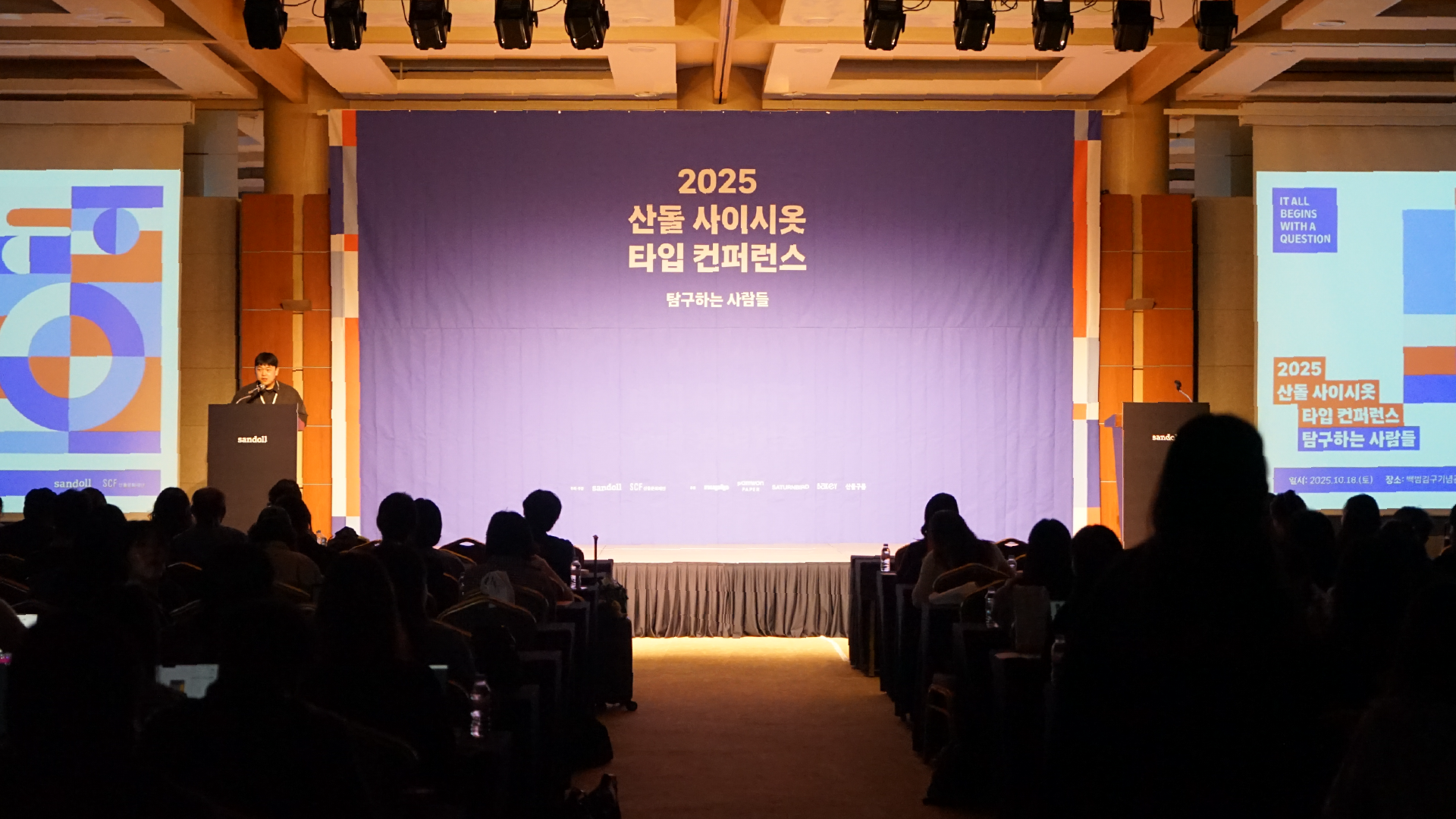
산돌은 누구나 자유롭게 표현할 수 있는 세상을 꿈꾸며 창작자들의 탐구를 지지하고 있어요. [2025 사이시옷]도 그 연장선상에서 기획됐어요. 우리의 철학을 담은 ‘탐구하는 사람들’이라는 주제는 ‘물음표’의 상징 기호로 표현했어요. 모든 탐구의 시작은 물음에서부터 시작함을 상징적으로 나타내고 있어요.
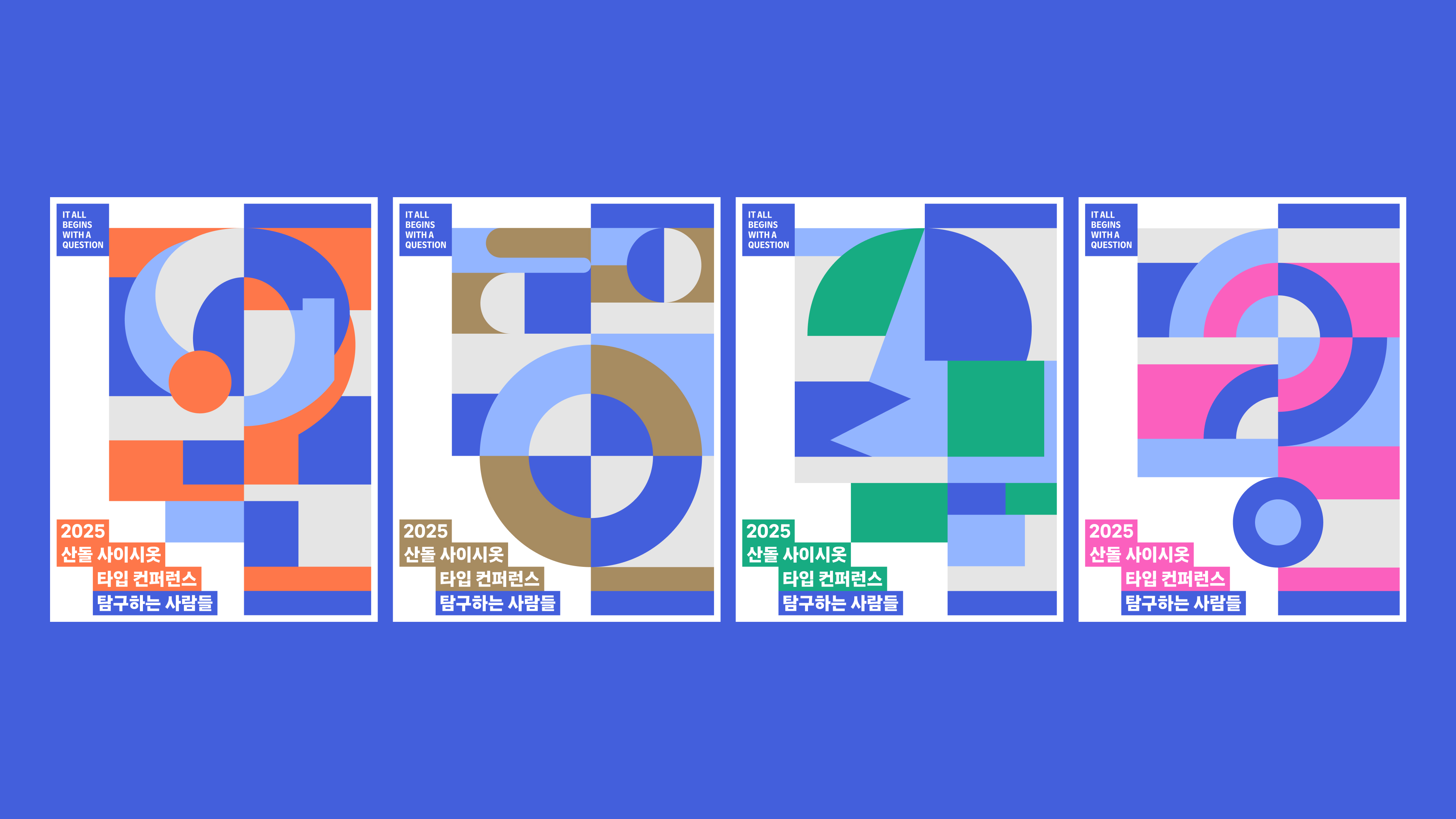
탐구자들
‘탐구’와 관련된 장치들을 행사장 곳곳에 설치했는데요. 그중 하나가 현장 등록 시스템이었어요. 특정 코드를 페이지에 심어 질문에 어떻게 답변하는지에 따라 탐구자 유형이 나뉘도록 설계했어요. 현장 등록을 마치고 나면 나의 탐구자 유형을 살펴볼 수 있었죠. 1. Risk-taker(모험가) 2. Tracer(관찰자) 3. Reframer(전환가) 4. Architect(분석가) 사이시옷의 탐구자 유형은 이렇게 4가지로 나뉘어요. 결과 페이지에서 탐구자 유형을 분석해 주고, 나와 잘 맞는 탐구자는 어떤 유형인지 제공했어요.
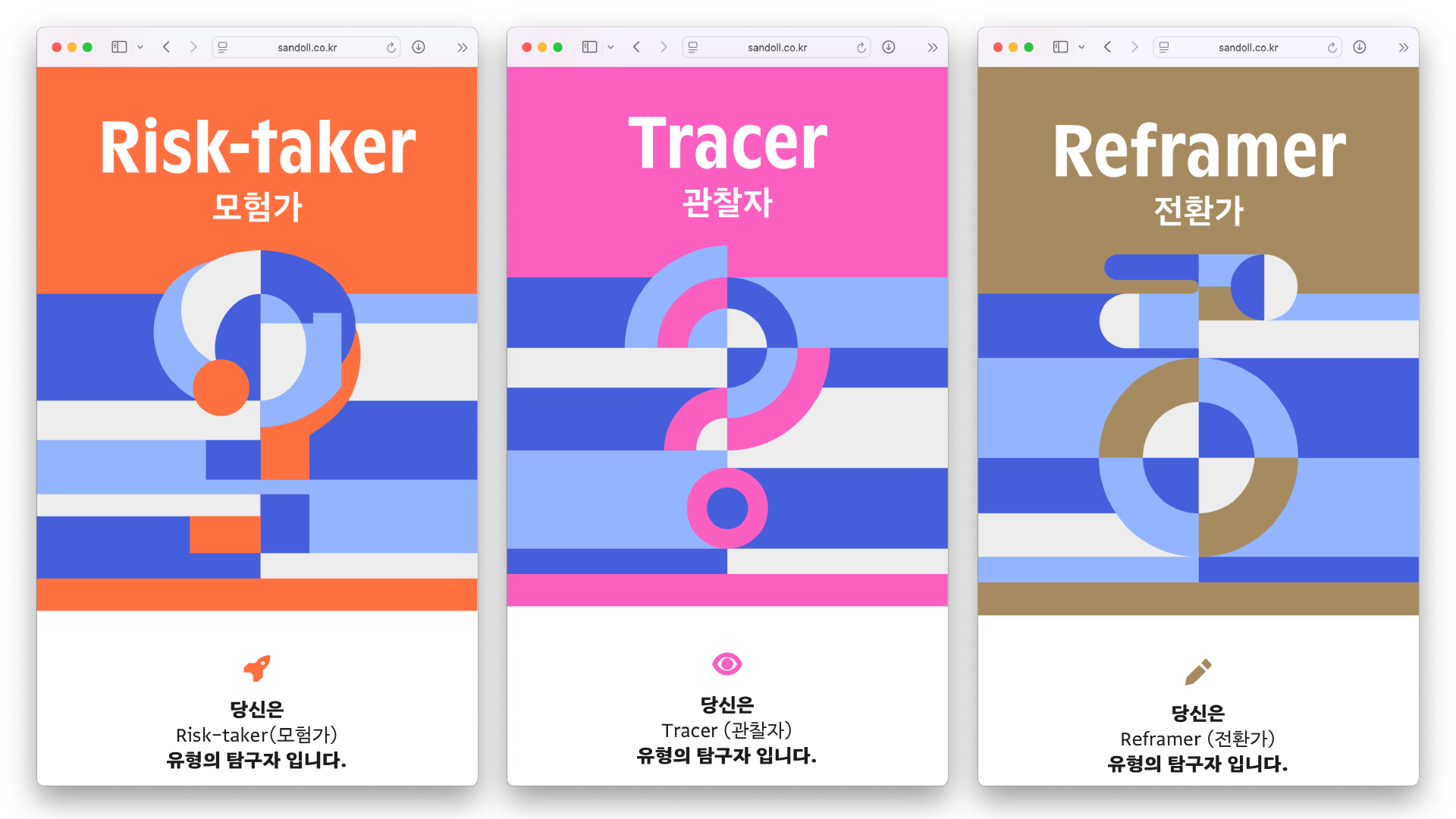
같이 탐구할까요?
[사이시옷]은 강연 외에도 다양한 방식으로 탐구의 경험을 확장하고 있어요. 참가자 간 자연스럽게 교류할 수 있는 접점을 만들기 위함인데요. 올해도 자유롭게 창작물을 부착할 수 있는 공유 보드인 ‘시옷보드’를 운영했어요. 포스터, 굿즈, 명함, 채용 정보 등 다양한 게시물들이 보드를 채웠어요. 창작물과 더불어 오늘의 다짐을 애정 어린 손 글씨로 남기며 각자의 생각을 공유하기도 했어요.
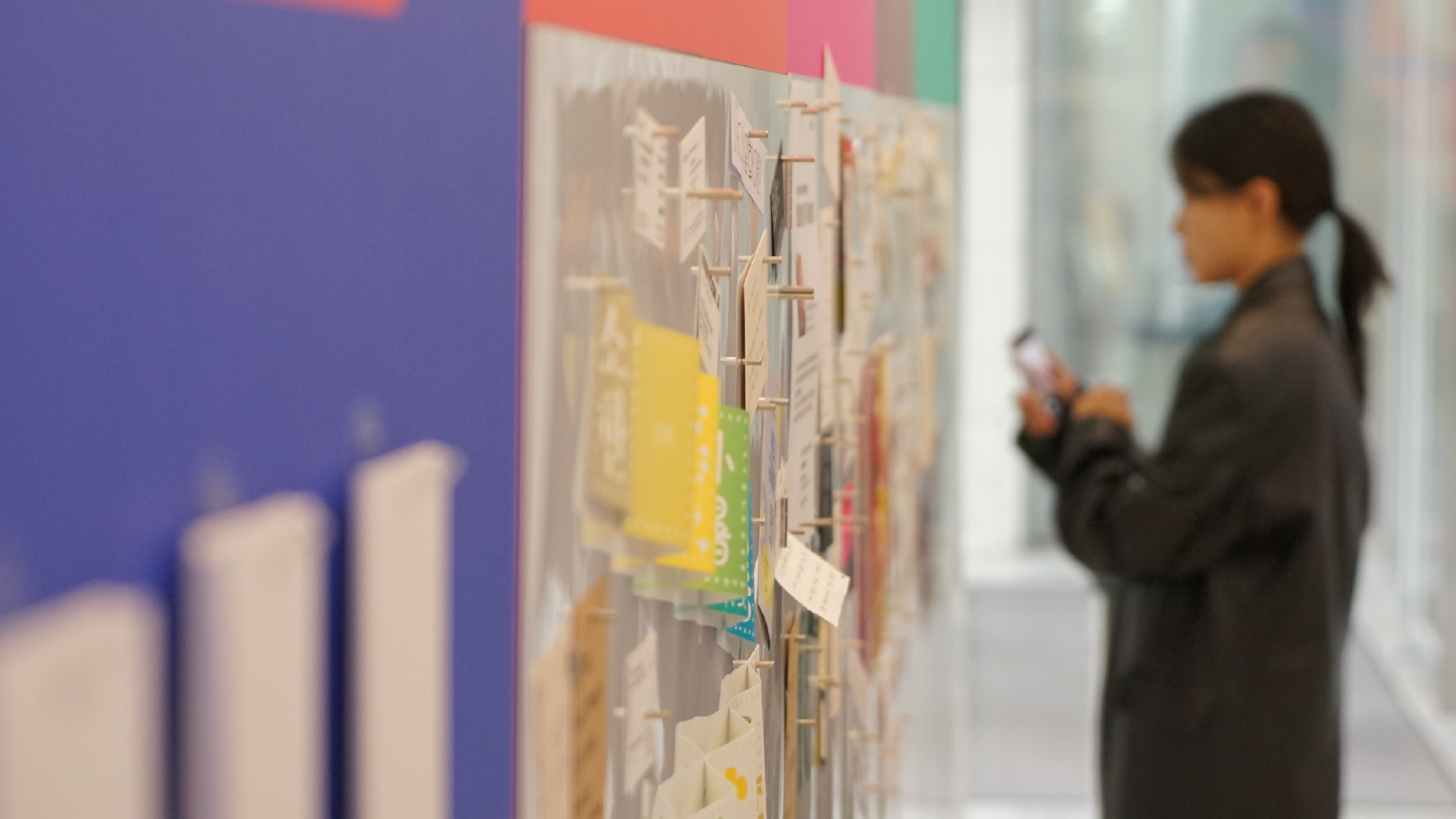
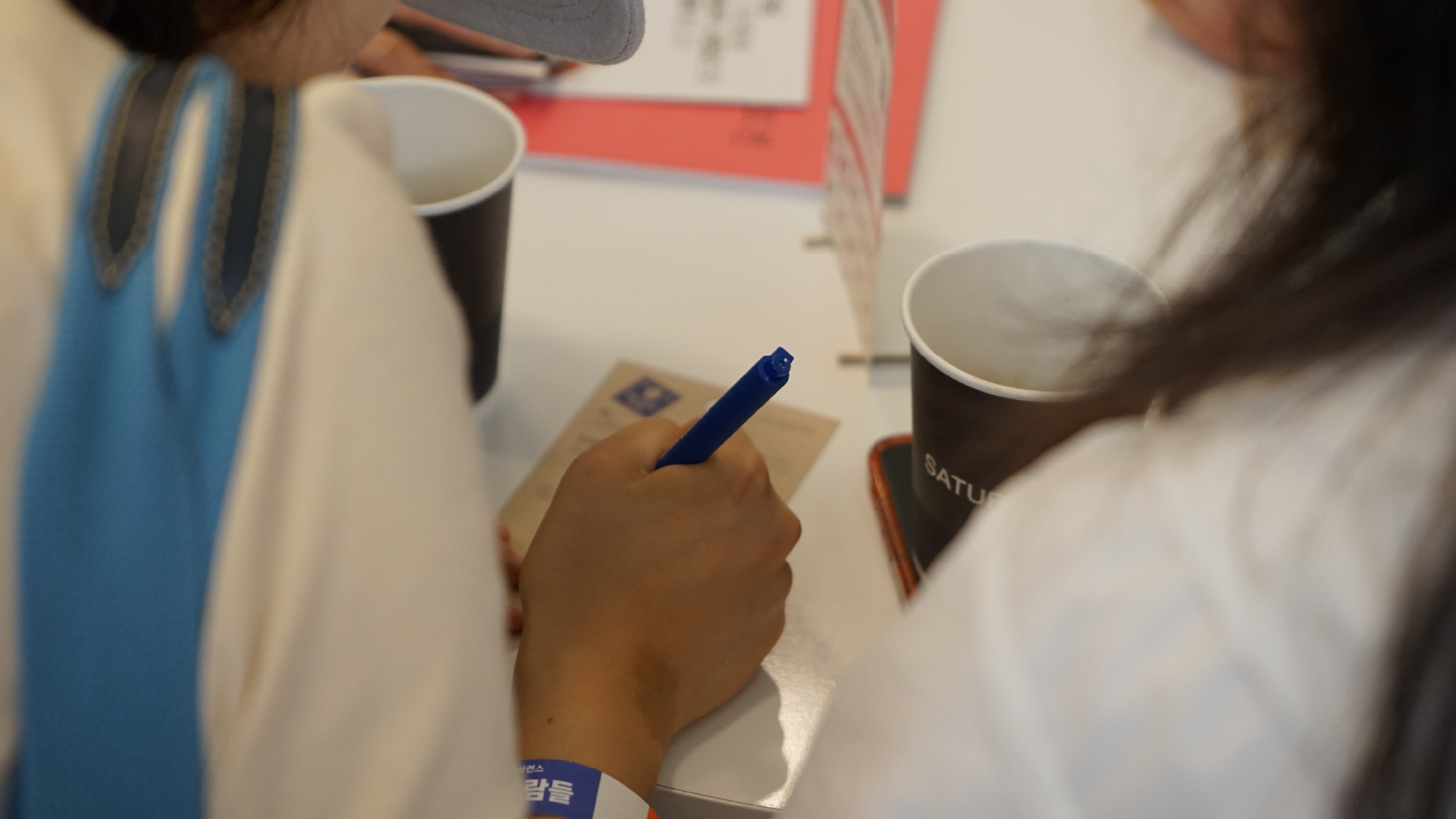
대면 네트워킹이 쑥스러운 분들을 위해 비대면으로 참여할 수 있는 장치도 마련했어요. 참가자들의 편지가 랜덤으로 교환되는 ‘레터박스’를 운영했는데요. 내가 쓴 편지를 투입하면 다른 참가자의 편지를 랜덤으로 받아볼 수 있는 시스템이에요. 서로의 얼굴은 모르지만, 같은 공간에서 같은 관심을 가진 사람들이 연결되는 경험이 묘하지 않나요? 산돌이 보유한 최첨단 인간 지능 기술로 구현할 수 있었던 ‘레터박스’였어요.
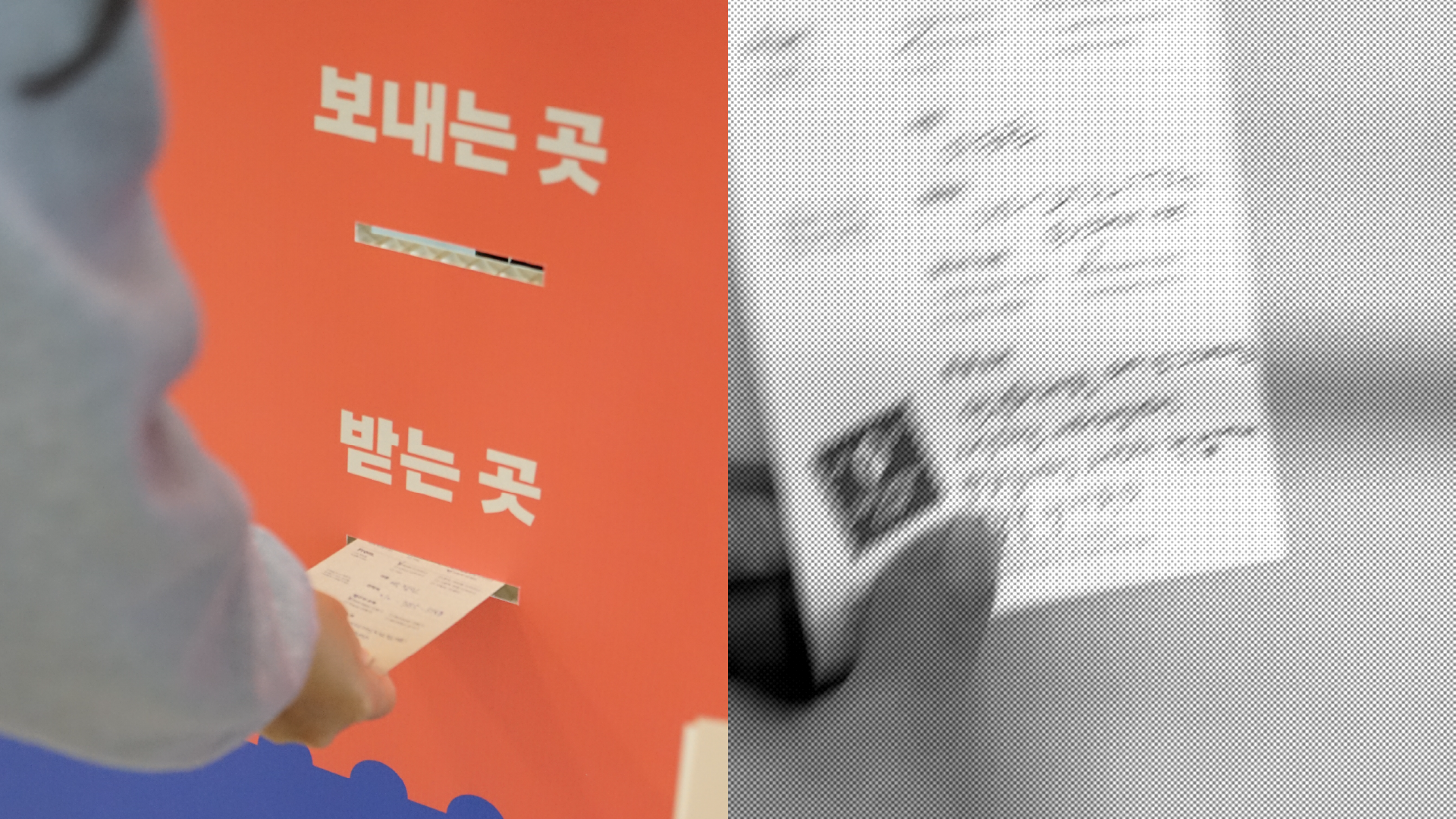
(좌)레터박스 외부 / (우)레터박스 내부, 편지를 분류 중인 인간 지능
[2025 사이시옷]은 다양한 브랜드가 함께 했어요. 30년 넘게 종이만을 연구해 온 삼원페이퍼, 독창적인 스타일링을 제안하는 누핍, 차원이 다른 커피 문화를 이끌어가는 새턴버드, 새로운 폰트 경험을 고민하는 베이키가 우리의 탐구에 동참했어요. 올해 [사이시옷]은 단순히 브랜드를 소개하는 자리를 넘어, 브랜드가 쌓아온 탐구의 결과를 여러분이 직접 경험할 수 있길 바랐어요. 다양한 탐구가 한자리에 어우러진 [2025 사이시옷]이 여러분에게 영감의 계기가 되었기를 바라요.
탐구하는 사람들
올해도 산돌의 탐구에 함께해 준 목소리들이 있어 [2025 사이시옷]을 완성할 수 있었어요. 무대에서는 각자의 자리에서 오랜 시간 탐구를 이어온 이들의 이야기를 들을 수 있었는데요. 이야기의 울림을 되새기며 [2025 사이시옷] 강연을 소개할게요.
아침의 빛, 한글 원전 활자를 다시 비추다 장가석(산돌 디자인스튜디오 타입디자이너), 황일선(민음사 미술부 북디자이너) | 첫 번째 강연은 11월 공개를 앞둔 산돌의 신규 폰트 「SD 초양」을 중심으로 진행됐어요. 「SD 초양」은 출판 업계 내 선호와 필요에 주목한 폰트예요. 제작에 참고한 옛 활자는 『조선말큰사전』에 사용된 본문용 서체였는데요. 이에 따른 옛 활자의 재해석과 제작 과정을 심도 있게 다루고, 실제 사용자인 민음사 출판부와 함께 개선 과정을 공유했어요.
‘활자를 디자인한다구?’ – 복원과 재해석 사이, 보이지 않는 축 위의 활짝명조 민본 (서울여자대학교 교수)
| 활자의 크기에 따라 달라 보이는 인상을 균질해 보일 수 있도록 하는 ‘옵티컬 사이징’에 대한 탐구를 나눴어요. 활자 시대 이후 사진 식자와 디지털 폰트 시대로 전환되면서 사라진 ‘옵티컬 사이징’을 한글에 적용한 「활짝명조」의 탐구 과정을 다뤘어요. 「활짝명조」는 최정호(제목용), 최정순(본문용), 박경서(각주용) 각각의 활자를 재해석한 것이 특징이에요. 산돌구름에서도 다루고 있으니 궁금하신 분들은 링크에서 자세히 볼 수 있어요.
핵심경험 전우성 (시싸이드 시티 대표)
| 브랜드가 넘쳐나는 시대, 고유함을 만드는 방법론을 탐구할 수 있는 시간이었어요. 제품과 가격으로 경쟁하는 시기를 지나 브랜드만이 제공할 수 있는 경험, 즉 ‘핵심경험’의 중요성을 알 수 있는 강연이었어요. ‘핵심경험’은 ‘기능적 핵심경험’과 ‘감성적 핵심경험’으로 구성되어 있는데요. 브랜드의 '핵심경험’을 발굴했던 케이스를 다루고, 메시지를 구체화하는 방법을 살펴볼 수 있었어요.
통합적 사고가 만드는 훌륭한 경험의 설계 송호성 (호라이즌유니온 대표)
| 통합적 관점은 브랜드, 프로덕트, 비즈니스를 포괄하는 개념으로, 각 축이 유기적으로 연결될 때 진짜로 의미 있는 경험을 만들 수 있음을 전했어요. 실제 사례를 통해 통합적 관점이 어떻게 적용되고 경험이 설계되는지를 다뤘어요. Ai 시대에 크리에이티브 디렉터의 역할을 정의하며 도구로써 AI와 협업하는 방법에 대한 고민을 나누기도 했는데요. 훌륭한 경험이란 무엇이며, 어떻게 만들어 지는지, 문제 해결의 방법은 무엇인지 등 다양한 노하우를 얻을 수 있었던 강연이었어요.
CFC의 탐구와 해석, 그리고 조형 전채리 (CFC 대표)
| “브랜드, 시장, 시대, 소비자에 대한 이해(Content)에 기반하여 브랜드만의 ‘다움’을 발견(Context)하고 이를 상징적인 형태(Form)로 담아내는 것” 강연 초반 등장한 CFC만의 아이덴티티 디자인 목표인데요. 고유한 철학을 바탕으로 최근의 CFC 작업을 살펴볼 수 있었어요. 헤리티지가 확고한 브랜드부터 정체성을 구축 중인 브랜드까지, CFC만의 감각을 녹여낸 사례들을 섬세하게 다룬 강연이었어요.
현대다운 언어 박이랑 (현대백화점 브랜드전략 팀장)
| 현대백화점의 시작부터 현재 이르기까지 ‘현대다움’이 쌓여온 과정을 살펴봤어요. 변화의 흐름 속에서 어떻게 체계를 다듬어 왔는지, 시행착오를 거치며 브랜드의 맥락을 만들어온 과정을 살펴볼 수 있었어요. 다양한 매체에서 현대백화점의 브랜드다움을 녹여낸 사례들을 바탕으로 ‘현대다움’이 만들어지는 과정을 살펴볼 수 있었던 강연이에요.
2025 사이시옷
올해의 [사이시옷]은 아침부터 저녁까지 긴 시간 이어졌어요. ‘탐구’가 브랜드와 창작자에게 어떤 힘이 되는지 보여준 시간이었어요. 기술이 발전해도 도구가 달라져도 탐구가 우리의 가장 단단한 축이 된다는 사실을 되새기며, ‘탐구’라는 태도를 다시 생각하게 되는 시간이었길 바라요.
[2025 사이시옷]에서 깊이 있는 이야기를 들려주신 연사도, 눈을 반짝이며 귀를 기울이며 경청하는 여러분도 모두가 ‘탐구하는 사람들’이었어요. 서로의 영역을 확장하고 배움을 얻는 경험이 우리를 더 멀리 이끌어 줄 것이라 믿어요. 다음 해에는 또 어떤 탐구를 마주하게 될까요? 2026년에도 새로운 물음으로 더 깊은 이야기를 함께 나눌 수 있길 바라며, 또 만나요!